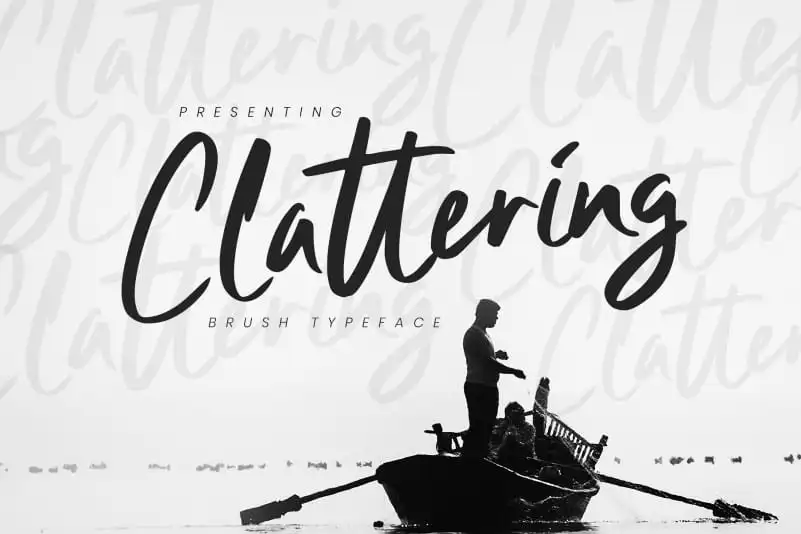
Clattering Brush Font – Download Grátis
A Clattering Brush Font é uma fonte de traçado à mão que traz a essência do estilo script para aplicações variadas. Desenhada pelo designer 178-MC, essa nova criação se destaca especialmente no campo dos títulos de comida e comércio, mas é versátil o suficiente para várias outras áreas. Com um traçado livre que transmite confiança entre curvas grossas e finas, ela parece uma obra feita à mão, repleta do peso de texturas naturais. Essa fonte perfeita para projetos de marca, logotipos, desenho de casamento, postagens nas redes sociais, anúncios, embalagem de produto, design de produto, etiquetas, fotografia, marcadores de água, convites e material de estaçãoaria. Seus traços espontâneos têm uma graça inconfundível que combina com a linguagem pessoal do estilo script. A Clattering Brush Font é perfeita para quem busca um toque de escrita natural em seus projetos gráficos, seja para criar uma identidade visual única ou dar vida ao design de produtos e publicações digitais.